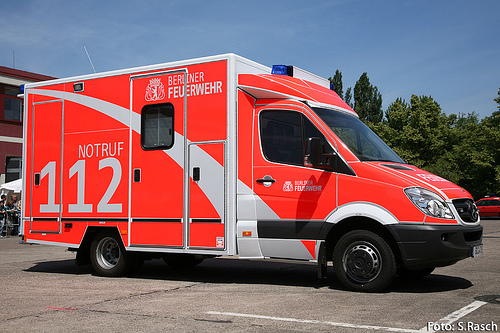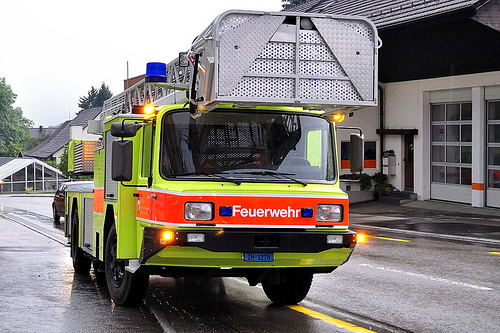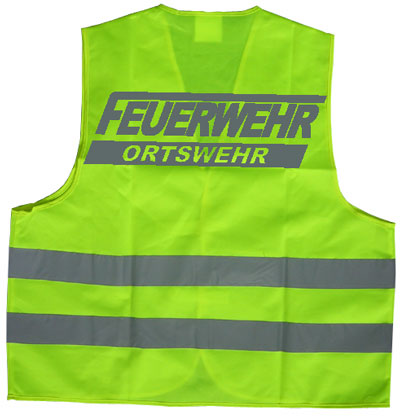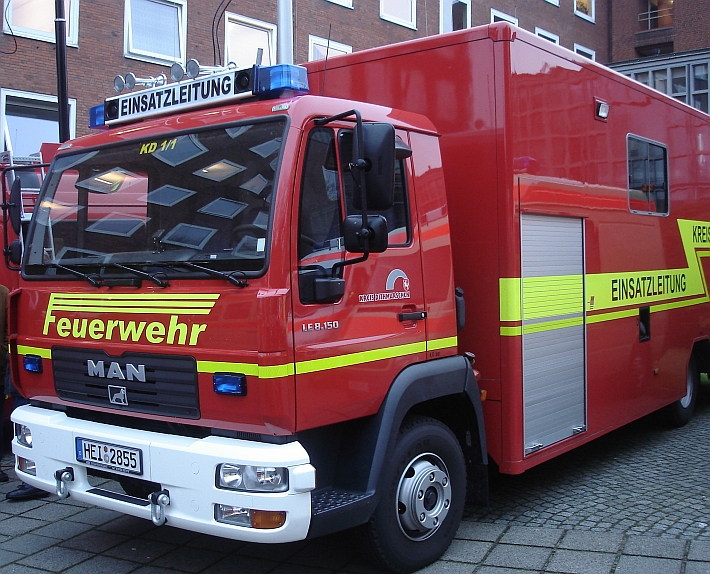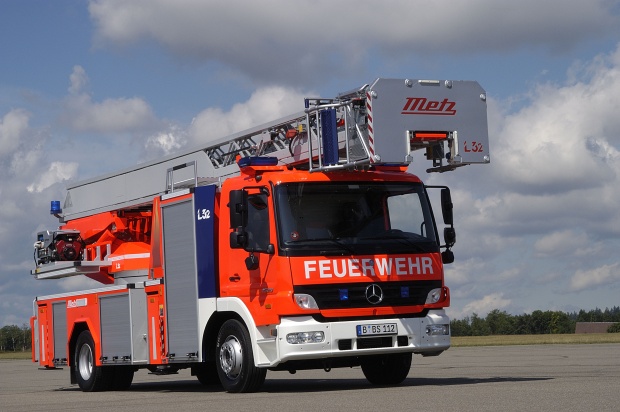
***TaTü—TaTa*** Beschriftung von Einsatzfahrzeugen.
angenommen ihr dürfet die beschriftung der örtlichen feuerwehrfahrzeuge übernehmen, welche schrift wäre für das wort 'FEUERWEHR' euer favorit? außerdem würden mich eure generellen meinungen zu diesen fragen interessieren:
muss eine solche schrift dynamisch (kursiv) aussehen?
sollte das wort feuerwehr in caps geschrieben werden?
in wie fern sind restliche beschriftungen (stadt-/gemeindewappen, notruf ...) wichtig?
sollte die schrift weiß auf rot sein oder sind neonfolien, reflexfolien vorzuziehen oder
sollte sich dies neon-/reflexfolien nur auf grafische gestaltung (linien und flächen) beziehen?
welche beschriftung von einsatzfahrzeugen ist euch positiv aufgefallen?
inwieweit ist spiegelverkehrte schrift auf der front eines fahrzeuges wichtig?
Wow. Das ist ja mal eine echt interessante Frage. Ich glaube, hierfür würde ich einen Klassiker nehmen, Helvetica oder so. Vielleicht auch eine fette Futura. Auf jeden Fall nichts aufregendes.
Nein. Ich denke, die Sirenen, das Blaulicht und die hohe Geschwindigkeit sind aufregend genug.
Ja, ich denke schon. Das ist aber wohl reine Gewohnheit. Ich bin ja sehr konservativ in solchen Sachen.
Das verstehe ich nicht.
Ich finde diese kunterbunten Krankenwagen die ich in der letzten Zeit häufiger sehe ganz schrecklich. Ich würde also von irgendwelchen Neonspielereien gänzlich absehen und einfach auf weiß auf rot setzen.
Da fällt mir nichts ein, und das ist gut so. Die Feuerwehr soll ja nicht ablenken.
Das würde mich jetzt auch interessieren. Ich halte das für ein nettes Feature. Gibt es dafür einen wichtigen Grund? Wenn man so einen riesigen Löschzug direkt hinter sich im Rückspiegel sieht, wird man doch auch so merken, dass das ein Feuerwehrfahrzeug ist, oder? Ich meine, es ist rot und macht viel Lärm.
Aber höre nicht auf mich, ich bin Zivilist. ^ ^
Dafür gibts ne DIN (kann ja in D auch garnicht anders sein ..)
DIN 14502-3 zu Farbgestaltung von Feuerwehrfahrzeugen
Ich glaube mich zu errinnern, dass die Beschriftung spiegelverkehrt aufgebracht ist, damit der Fahrer im Rückspiegel dann gleich das Wort „FEUERWEHR“ lesen kann und so schneller den Weg frei macht.
das ist auch toll, aber da hält sich halt keiner dran, wie es in D üblich ist kocht jeder sein eigenes süppchen. ich finde ja auch das solche fahrzeuge deutschlandweit gleich aussehen sollten — aus grafiker sicht bin ich natürlich frph das es nicht so ist ;)
das war mir schon klar, aber in wie fern ist das wichtig. ich meine - sieht man die aufschrift im rückspiegel wirklich? dies wäre ja nur der fall wenn man die musik extrem laut hat, oder kopfhörer im auto nutzt, ansonsten schaut man ja schon in den rückspiegel sobald man die sirene hört.
das ist natürlich nicht zur allgemeinen belustigung gedacht, sondern zur optischen erkennung. gerade die französischen fahrzeuge sind mit ihrem linienmuster große vorbilder. die frage ist nur: das feuerwehrauto ist rot, laut und groß — wie kann man sowas nicht als feuerwehrauto wahrnehmen?
So viele Verwechslungsmöglichkeiten bestehen bei einem großem roten Auto mit Blaulicht eigentlich nicht. Außerdem sind andere Verkehrsteilnehmer nur verpflichtet sofort freie Bahn zu schaffen, wenn Blaulicht und Einsatzhorn gemeinsam verwendet werden (§ 38, StVO). Aus diesem Grunde werden auch vermehrt Frontblitzer im Kühlergrill verbaut, damit PKW-Fahrer einen LKW im Einsatz hinter ihnen wenigstens optisch besser wahrnehmen können.